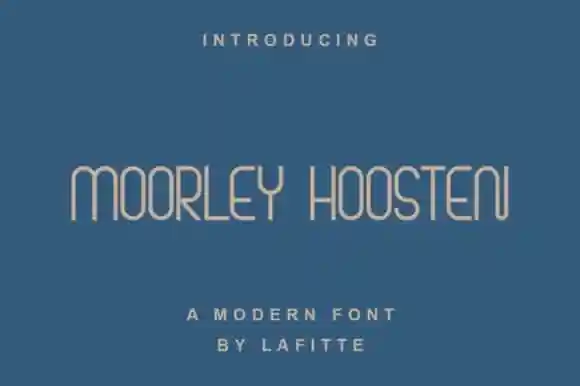
Moorley Hoosten Sans Serif Font – Download Grátis
A ‘Moorley Hoosten Sans Serif Font’ é uma escolha perfeita para quem busca simplificação e modernidade no seu design. Criada pelo designer lafitte 58, essa nova versão de tipo sans-serif apresenta linhas duras e curvas suaves, com ângulos arredondados. Esta fonte original não só trará uma identidade visual distintiva a seus projetos, mas também será muito versátil – adequada para aplicativos como letras de documentos, títulos, logotipos ou até mesmo embalagens de produtos. Sua estética minimalista combina perfeitamente com os mais variados formatos e propósitos gráficos, tornando-a uma fonte indispensável para designers de todos os gostos. Seja você um estiloso criador de materiais empresariais ou alguém que busca simplicidade em seus designs internautas, a ‘Moorley Hoosten Sans Serif Font’ é certamente o recurso gráfico perfeito para sua necessidade.